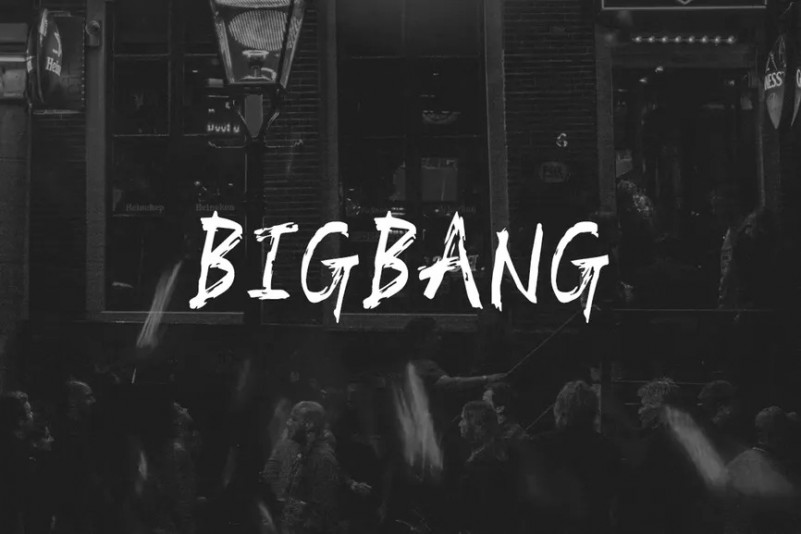
BIGBANG Font
La police unique fait main de pinceau personnalisé adapté à tous les besoins de conception : image de marque, Logos, citations manuscrites, emballage de produit, marchandise, conception de blog, conception de la publicité moderne, invitation, Graffiti, Citation d’art, décoration d’intérieur, Livre/Cover Titre, Invitation, événements spéciaux, anniversaire, tasse personnalisée, oreiller, t-shirts, tous les besoins de conception de lettrage de pinceau et plus encore.